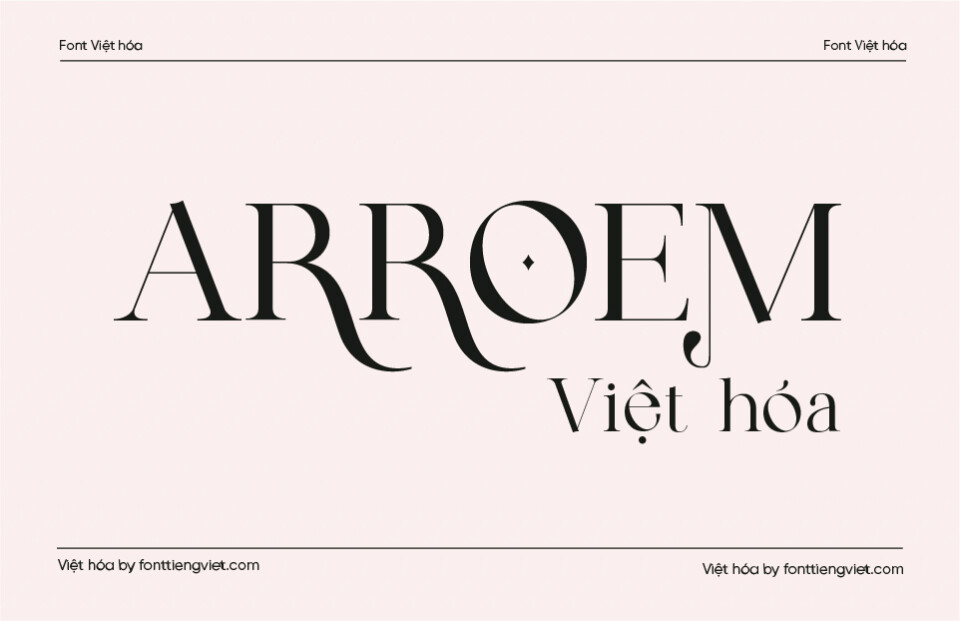
Tải Ngay Font Việt hóa 1FTV VIP Arroem Miễn Phí Cho Thiết Kế Sáng TạoGiới thiệu về bộ Font Việt hóa 1FTV VIP Arroem chuyên nghiệpTrong thế giới thiết kế đồ họa hiện đại, việc lựa chọn một bộ phông chữ phù hợp đóng vai trò then chốt trong việc truyền tải thông điệp và cảm xúc của tác phẩm. Font Việt hóa 1FTV VIP Arroem là một trong những lựa chọn hàng đầu dành cho các nhà thiết kế đang tìm kiếm sự kết hợp hoàn hảo giữa nét cổ điển và tính ứng dụng cao. Khi nhắc đến Font Miễn Phí, người dùng thường mong đợi một bộ gõ ổn định, không lỗi dấu và mang tính thẩm mỹ cao. Bộ font Arroem này hoàn toàn đáp ứng được những kỳ vọng đó với các đường nét được chăm chút kỹ lưỡng, phù hợp với nhiều phong cách thiết kế khác nhau từ đơn giản đến sang trọng.Đặc điểm nổi bật của Font Việt hóa 1FTV VIP ArroemThiết kế tinh tế và hiện đạiBộ Font Việt hóa 1FTV VIP Arroem sở hữu cấu trúc chữ thanh thoát, các nét uốn lượn mềm mại nhưng vẫn giữ được sự cứng cáp cần thiết. Điều này giúp cho phông chữ không chỉ đẹp mắt trên các bản in mà còn hiển thị cực kỳ sắc nét trên các thiết bị kỹ thuật số. Đặc biệt, quá trình Việt hóa đã được thực hiện tỉ mỉ, đảm bảo các dấu câu trong tiếng Việt được đặt đúng vị trí, không bị đè nét hay méo mó khi gõ văn bản dài. Đây là điểm cộng lớn cho các bạn học sinh, sinh viên khi làm bài thuyết trình hoặc thiết kế báo tường số.Khả năng ứng dụng đa dạng trong thực tếBạn có thể sử dụng 1FTV VIP Arroem cho rất nhiều mục đích khác nhau. Trong lĩnh vực giáo dục, font chữ này giúp các tiêu đề bài giảng trở nên thu hút hơn. Trong kinh doanh, nó là lựa chọn tuyệt vời cho thiết kế logo, banner quảng cáo hay bao bì sản phẩm cao cấp. Sự linh hoạt của bộ font này cho phép người dùng tự do sáng tạo mà không lo bị giới hạn về phong cách. Từng con chữ đều mang lại cảm giác dễ chịu cho người đọc, giúp nội dung được truyền tải một cách tự nhiên và ấn tượng nhất.Lợi ích khi sử dụng font chữ đã được Việt hóaTiết kiệm thời gian và tối ưu hiệu quả công việcViệc sử dụng các bộ font đã được Việt hóa sẵn như Arroem giúp người dùng loại bỏ hoàn toàn nỗi lo lỗi font khi gõ tiếng Việt. Thay vì phải mất công chỉnh sửa từng ký tự hay tìm cách thay thế dấu, bạn chỉ cần cài đặt và bắt đầu gõ. Điều này không chỉ giúp tiết kiệm thời gian mà còn đảm bảo tính nhất quán cho toàn bộ bản thiết kế. Một bộ font chất lượng sẽ giúp bạn tạo nên sự khác biệt và chuyên nghiệp ngay từ cái nhìn đầu tiên.Tương thích tốt với các phần mềm đồ họaFont Việt hóa 1FTV VIP Arroem có độ tương thích cao với hầu hết các phần mềm thiết kế phổ biến hiện nay như Adobe Photoshop, Illustrator, Canva hay thậm chí là các ứng dụng văn phòng như Word và PowerPoint. Quy trình cài đặt đơn giản, chỉ cần vài thao tác chuột là bạn đã có ngay một công cụ mạnh mẽ trong bộ sưu tập của mình. Việc sở hữu những phông chữ VIP như thế này giúp kho tài nguyên của bạn phong phú hơn bao giờ hết.Kết luận và hướng dẫn tải fontHy vọng rằng bộ Font Việt hóa 1FTV VIP Arroem sẽ trở thành người bạn đồng hành đắc lực trong các dự án sắp tới của bạn. Việc đầu tư vào font chữ là bước đi thông minh để nâng tầm giá trị hình ảnh. Đừng quên ghé thăm trang web của chúng tôi thường xuyên để cập nhật thêm nhiều bộ Font Miễn Phí, Font Việt Hóa, Font Việt hóa 1FTV VIP Arroem độc đáo khác. Hãy bắt đầu sáng tạo ngay hôm nay với những nét chữ tinh tế và đậm chất nghệ thuật mà bộ font này mang lại cho bạn.
Font Việt hóa 1FTV VIP Arroem